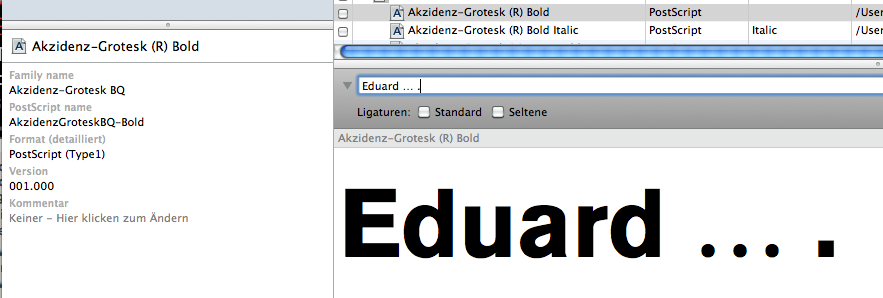
Akzidenz Grotesk: Runde oder eckige Auslassungspunkte?
Ich bastle gerade eine Broschüre mit der Akzidenz-Grotesk von Berthold. Beim Feintuning ist mir aufgefallen, dass die Auslassungspunkte (…) rund statt quadratisch sind. Merkwürdig. Bei der Adobe Akzidenz-Grotesk sind diese – meiner Meinung nach richtig – eckig.
Hat sich der Großmeister Günter Gerhard Lange was dabei gedacht oder nur gepennt?
Ich meine den Berthold-Quality Font von 1992. Da sind die Punkte rund. Ich mache in der Firma mal ein Muster.
Die runde Punkte finde ich auch komisch …
Im Blei sind die Punkte eckig; die Auslassungspunkte wurden grundsätzlich nicht extra gegossen sondern aus Einzelpunkten zusammengesetzt, weswegen es schon seltsam ist, wenn die eine andere Form haben sollten als die regulären Punkte:
Sie sehen komisch aus, diese Auslassungspunkte, oder?
Und sie scheinen auch kleiner angelegt zu sein als die ursprünglichen eckigen Satzende-Punkte.
Meine AG von Berthold ist wohl die gleiche wie Bertels. Bei myfonts gibt es die richtigen Punkte zur AG. Ob das was mit „Qualität“ zu tun hat? :nana:
Es gibt keine dummen Fragen? Von wegen... Beweis:
Könnte es vielleicht sein, daß das, was der Kollege als Auslassungspunkte ansieht, in Wirklichkeit ein Linienelement von einer punktierten Linie ist? Aber wahrscheinlich werden punktierte Linien mit Euren Programmen gar nicht aus Einuzelelementen gebaut wie im Photosatz.
Typografski hat die BE-Fassung, die müßte ja Adobe digitalisiert haben.
Ich habe wie Sharif und Bertel die BQ-Fassung von ’92. Da sind nicht nur die Auslassungspunkte rund, sondern auch die Puntke im Teilungszeichen:
… und in der Palatino von ’92 sind genau diese beiden Zeichen ebenfalls enthalten!
(Die Zeichen sind wirklich völlig identisch, hier ist nur wegen der geringen Auflösung ein Unterschied sichtbar.)
Vermutlich gibt’s noch ein paar mehr Sonderzeichen (ich habe jetzt nicht alle Zeichen nachgesehen), die man bei Berthold der Einfachheit halber in alle Schriften übernommen hatte. Fragt sich nur: Zu welcher Schrift gehören sie ursprünglich? :?